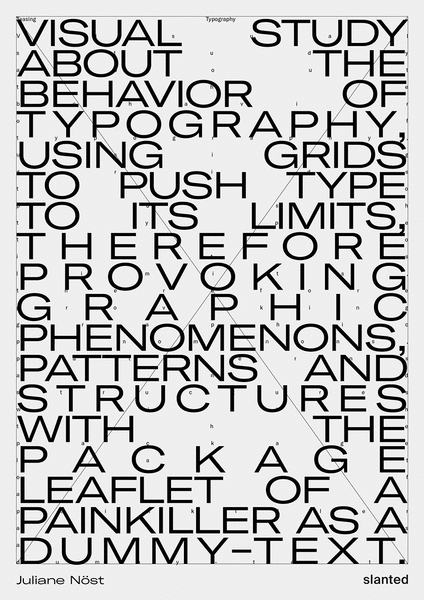
Teasing Typography
Wie verhält sich Typografie unter extremen Bedingungen? Welche visuellen Phänomene, Muster, Artefakte und grafischen Elemente können provoziert werden, wenn man die Schrift durch extreme Raster schiebt und extreme typografische Parameter verwendet? An welchem Punkt kehrt ein Text zu seinem ursprünglichen Zweck zurück, den Leser zu informieren? Wann wird Text zu etwas anderem: einem grafischen Element, einer grauen Fläche, einem statischen Geräusch oder einem haptischen Muster?
Um diesen Fragen nachzugehen, schob die Grafikdesignerin Juliane Nöst im Rahmen einer typografischen Studie systematisch Text durch verschiedene Raster. Ausgehend von den InDesign-Standardeinstellungen wurden verschiedene Schriftgrößen und Spalten verwendet, um ein breites Spektrum an unterschiedlichen typografischen Ergebnissen zu erzeugen.
In einem weiteren Schritt wurden bestehende Ergebnisse überlagert und collagiert, mit dem Ziel, zusätzliche Sätze von unerwarteten Formen und Grafiken zu erzeugen. Das Ergebnis dieser Forschung führt zu einer Vielzahl von visuellen Besonderheiten, die absorbierende Muster erzeugen, mit den Rastern interagieren, sie manchmal sichtbar machen, während sie unter anderen Parametern verschwinden.
Das 500-seitige Buch gibt einen Einblick in die unendlichen Möglichkeiten der Gestaltung mit Typografie.